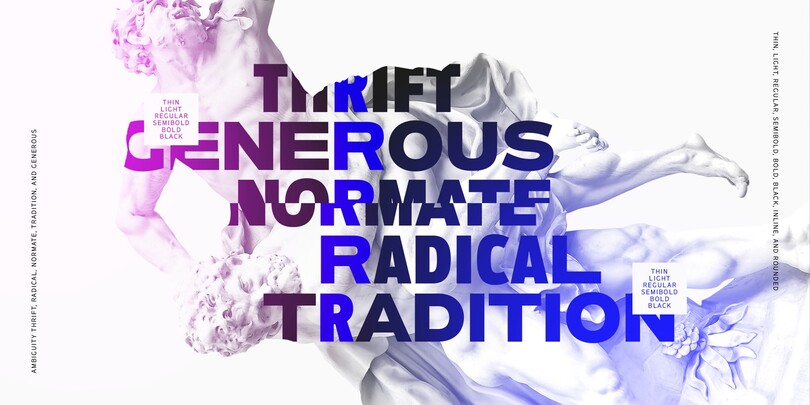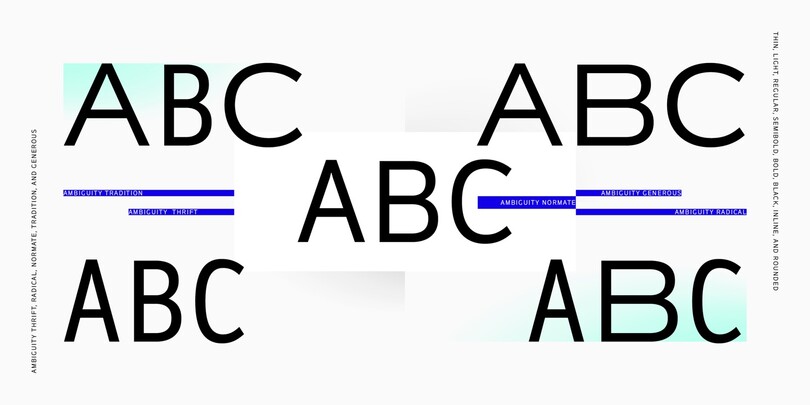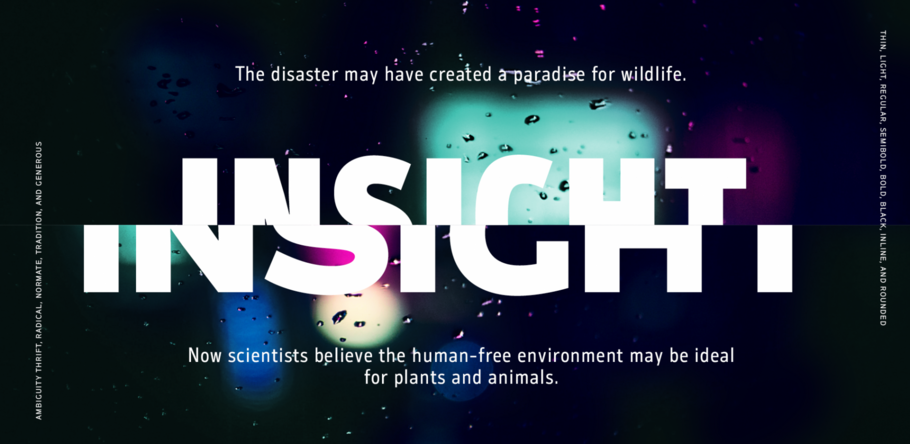
Ambiguity, une police et cinq personnalités.
“ Ambiguity offre cinq personnalités - idées - convictions - qui fonctionnent aussi parfaitement ensemble. ”
Ambiguity est une famille typographique avec cinq personnalités ou « états » distincts, créée comme un outil pour inviter les designers et les marques à sortir de leur zone de confort. Elle englobe à la fois la tradition et la radicalité, ainsi que la générosité et la modération, et nous encourage à remettre en question nos croyances sur l’intersection du style et du sens.
« Ambiguity a démarré comme une expérience de pensée », raconte Charles Nix, qui a commencé à révolutionner les idées du design en 2016, après avoir écouté la conférence de Paola Antonelli à Toronto. Antonelli, conservatrice principale au MoMA, a affirmé que l’utopie est à portée de main si nous adoptons l’ambiguïté, la fluidité et le flux comme états de perfection. « Elle a illustré ce point avec une collection d’œuvres défiant les frontières - entre design et science, homme et machine, technologie et nature, et genres », explique Nix. « Le challenge et la promesse de transformer le monde en changeant notre cadre de référence ont résonné en moi. C’est une partie essentielle du processus et des produits du design. »
C’est dans cet esprit que Nix a commencé à jouer avec les proportions des lettres. Il a délibérément inversé et recombiné les proportions traditionnelles pour défier ses propres a priori. L’exploration a finalement abouti à cinq différents « états » pour Ambiguity : Tradition, Radical, Thrift, Generous et Normate. Ensemble, ils offrent des opportunités variées d’explorer l’interaction de la forme typographique et du contenu.
Tradition est conservatrice, s’appuyant sur des formes de lettres historiques. Radical rejette les idées héritées de la proportion, élargissant les formes de lettres typiquement élancées, et inversement. « C’est une anticonformiste », explique Nix. Thrift cherry reprend les formes condensées de Tradition et Radical, tandis que Generous fait de même pour les formes larges. Normate se trouve au centre, un mélange synthétique de toutes les autres.
« Tradition est très réconfortante », détaille Nix. « C’est le masque du conservatisme. Elle apaise parce qu’elle offre les proportions que nous attendons d’elle. Thrift tient mieux dans un espace réduit, donc elle convient bien là où les mots veulent devenir grands, comme des titres gigantesques, ou là où le texte doit s’entasser, comme une police pour petit écran. La variante Generous donne un sentiment d’insouciance et de luxe. On pourrait s’attendre à ce que la Radical soit utilisée d’une manière un peu dadaïste, mais dans un contexte classique, elle procure un agréable électrochoc. »
Ambiguity est un test concluant. Les designers pourraient passer des heures à essayer des polices de caractères qui n’offrent qu’une seule de ces voix. Ambiguity offre cinq différentes personnalités - idées - convictions - qui fonctionnent aussi parfaitement ensemble.
Charles Nix.
Charles Nix
Charles Nix, designer, typographe et conférencier, est actuellement directeur typographe chez Monotype Studio. Il a créé pour la bibliothèque Monotype le design d’un certain nombre de fontes de caractères populaires, dont Walbaum et Hope Sans, qui ont reçu un « Certificat d’excellence typographique » lors du 22e concours annuel de design typographique Type Directors Club. Il a également réalisé des fontes personnalisées pour Google Noto, Progressive Insurance et le Philadelphia Museum of Art.